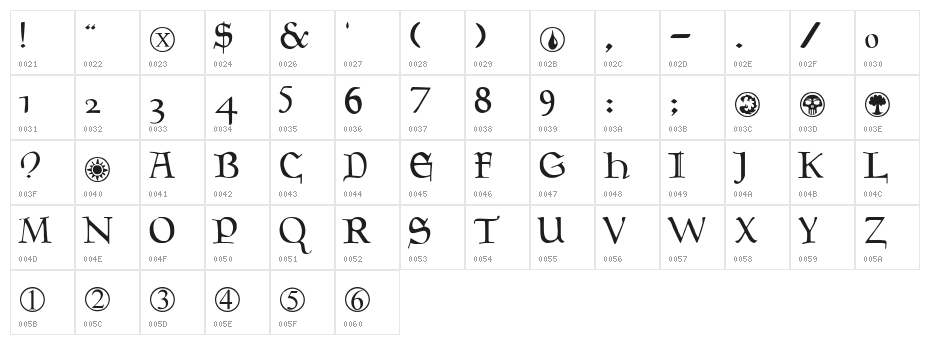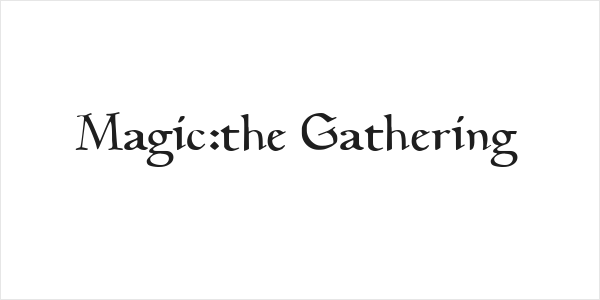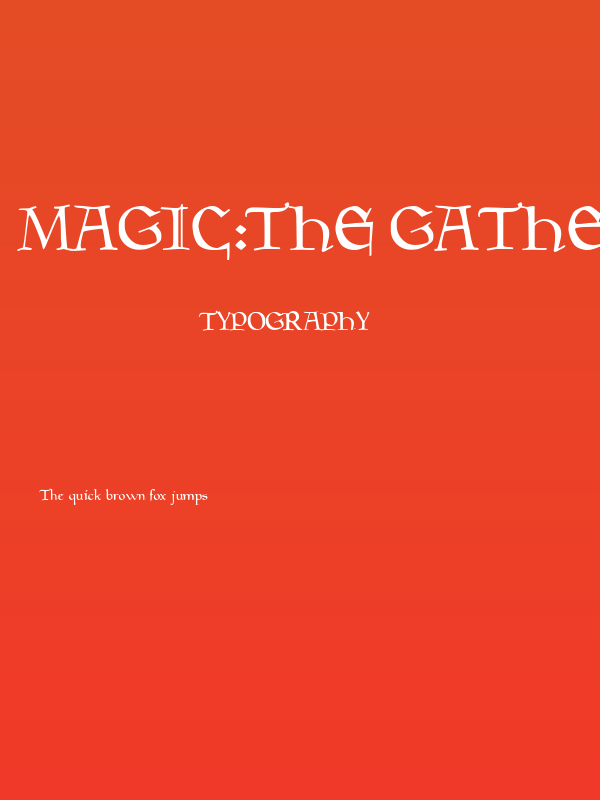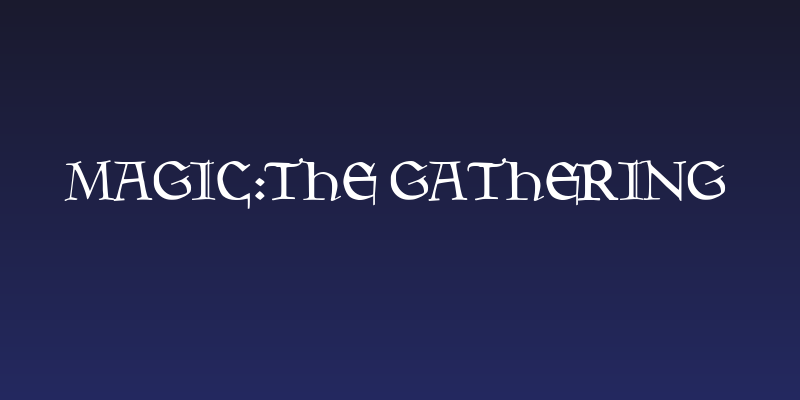
Magic:the Gathering Font
✎ Script
| 分类 | Script |
| 整体风格 | Fantasy, Medieval, Dramatic |
| 使用场景 | Headlines, Logos, Book Covers |
| 推荐项目 | Ideal for fantasy-themed projects, game titles, book covers, and branding that requires a mystical or medieval touch. |